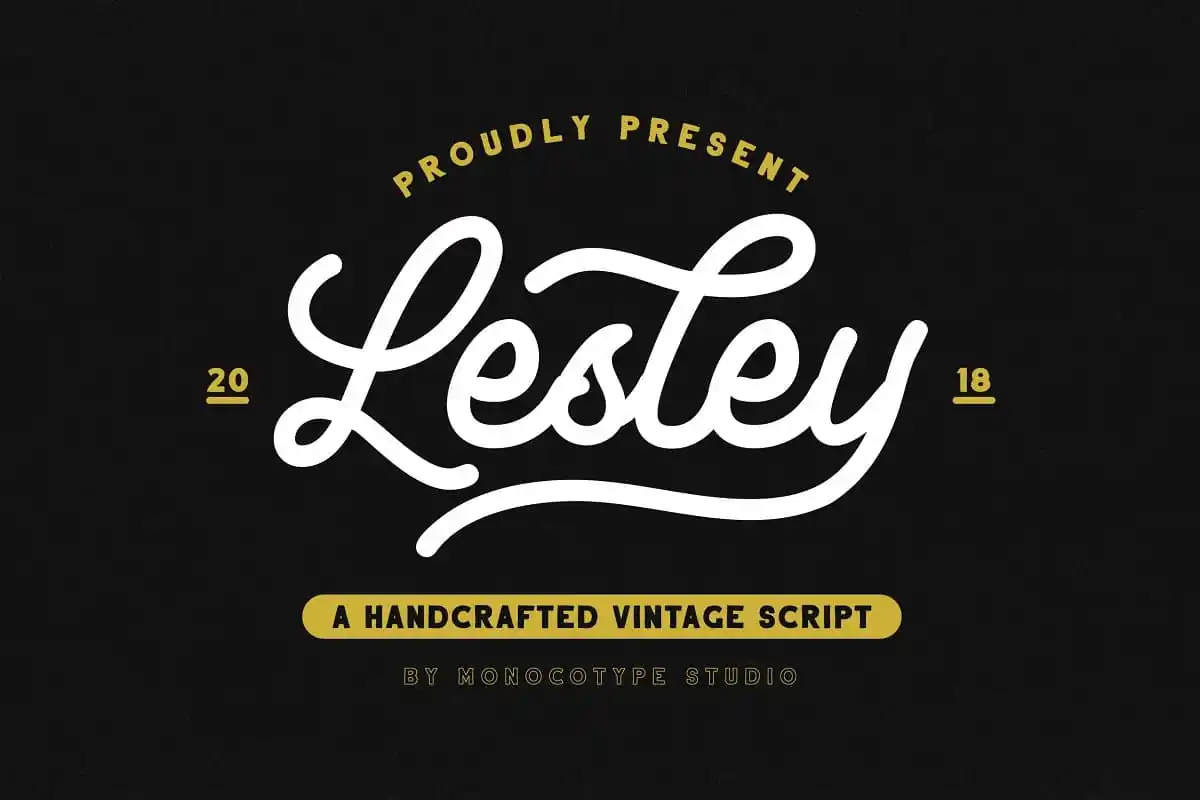
Lesley Monoline Script Font – Download Grátis
A Lesley Monoline Script Font é a escolha perfeita para quem busca uma fonte script vintage, cheia de personalidade e estilo único. Com suas linhas finas e extremamente elegantes inspiradas nas estilosas criações dos anos 40 e 50, esta fonte oferece um toque delicado de nostalgia ao seu design. A Lesley Monoline Script é um monoline script que se destaca por sua consistência e sofisticação, perfeitamente adaptada para aplicativos como logotipos, rótulos, adesivos, flyers ou até mesmo camisetas customizadas. Os recursos de OpenType aprofundam ainda mais essa experiência, com alternativas estilísticas, swashes, ligaturas, conjuntos estilísticos e formações ornamentais que permitem uma mistura única de letras para combinar perfeitamente com seu estilo. Seja você um designer gráfico criativo ou simplesmente alguém buscando imprimir seus próprios designs em camisetas, a Lesley Monoline Script é uma excelente opção para agregar um toque diferenciado e único ao seu trabalho.